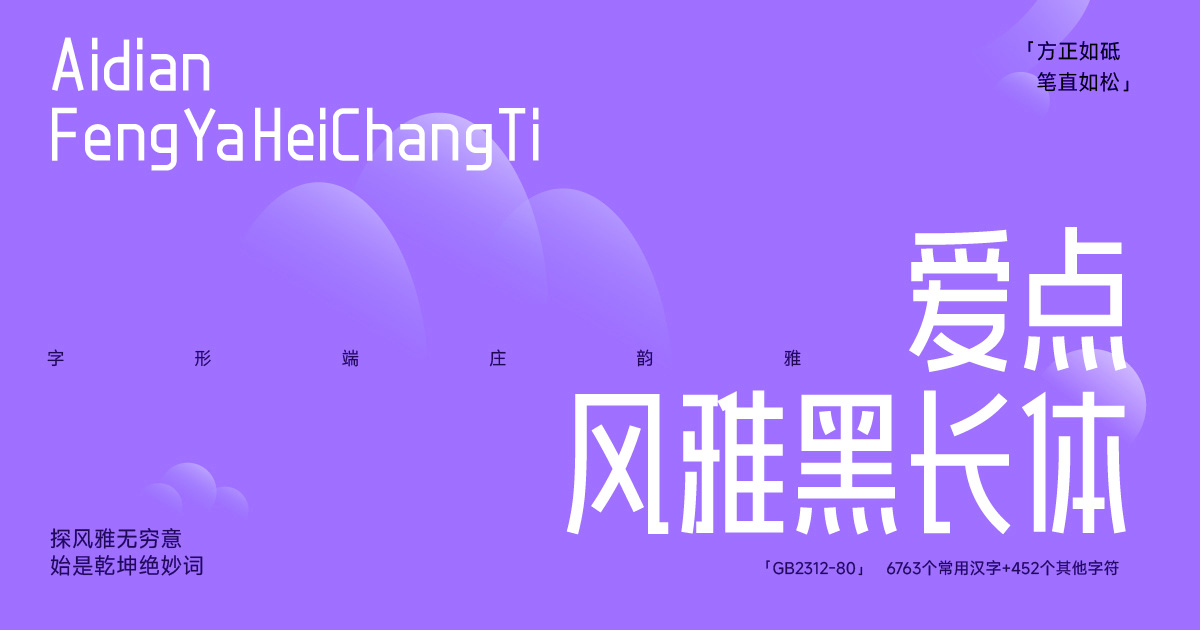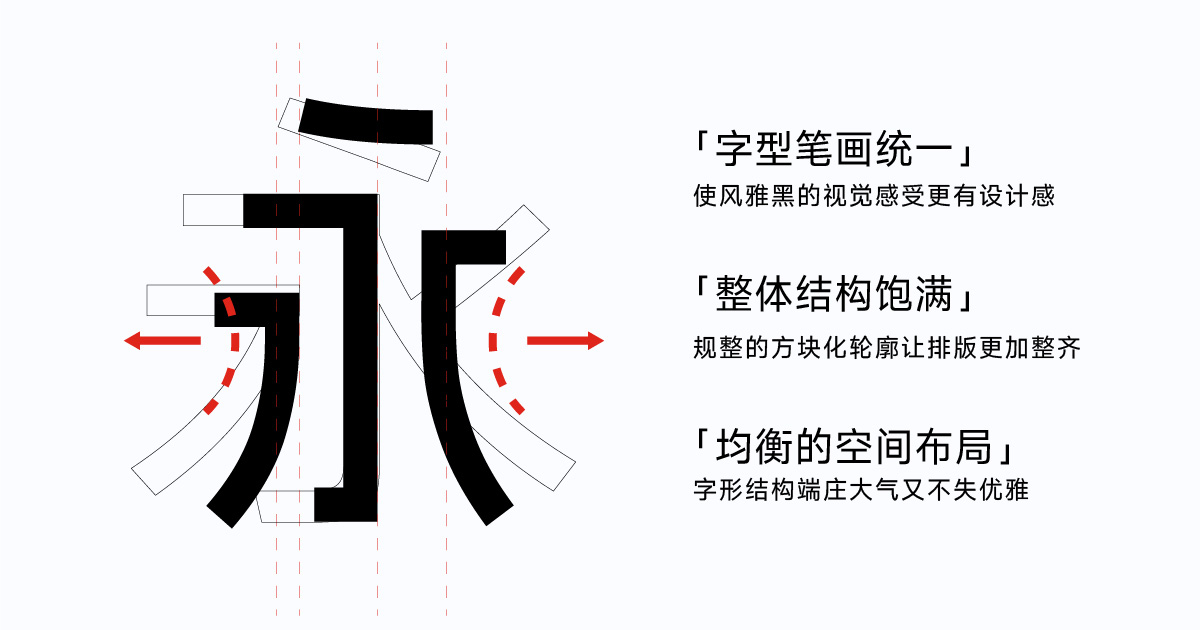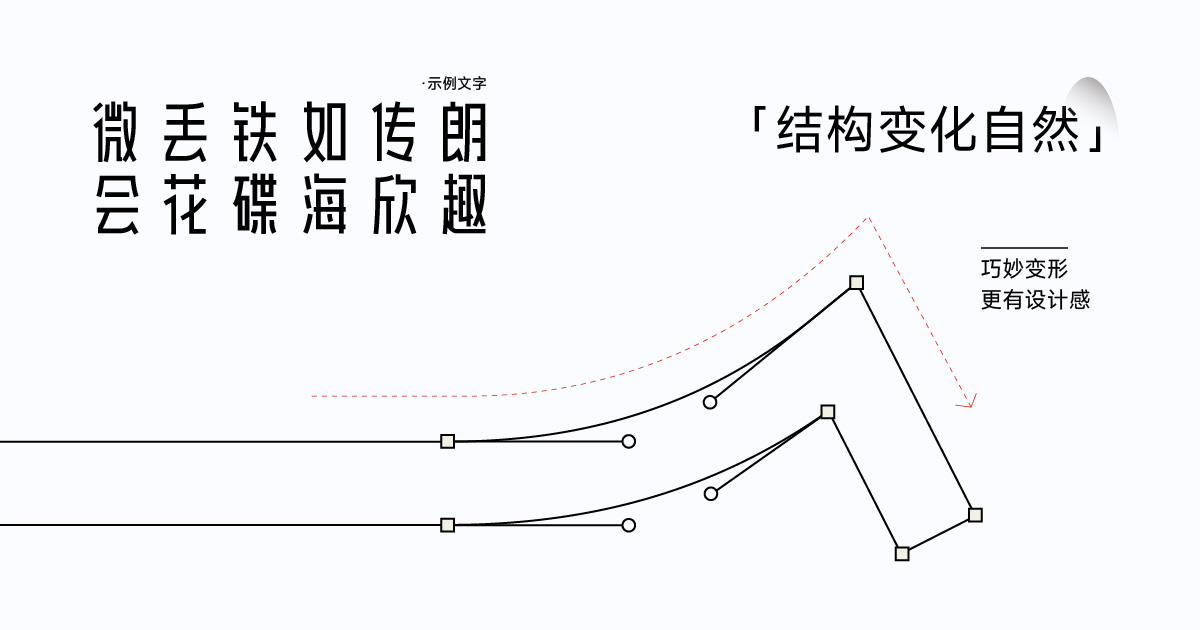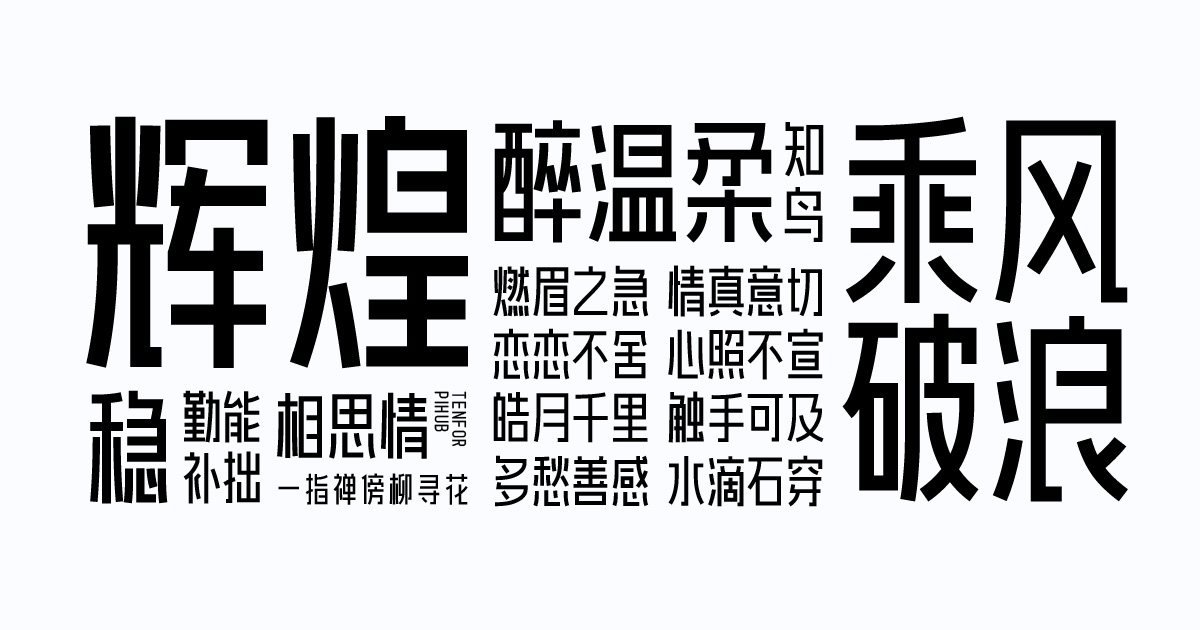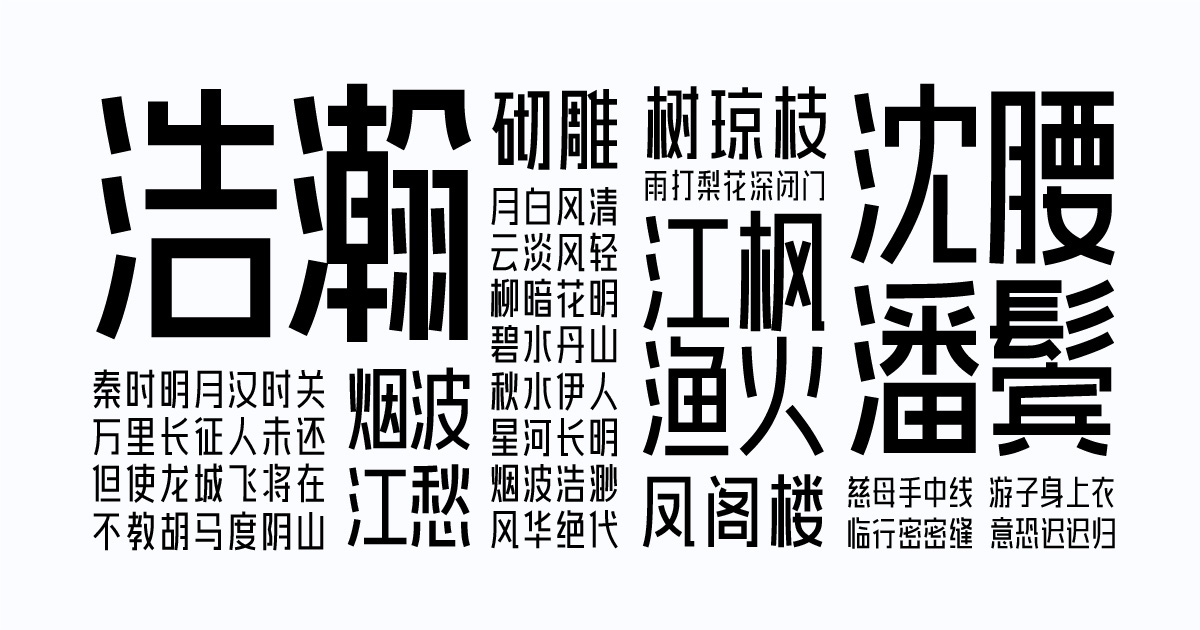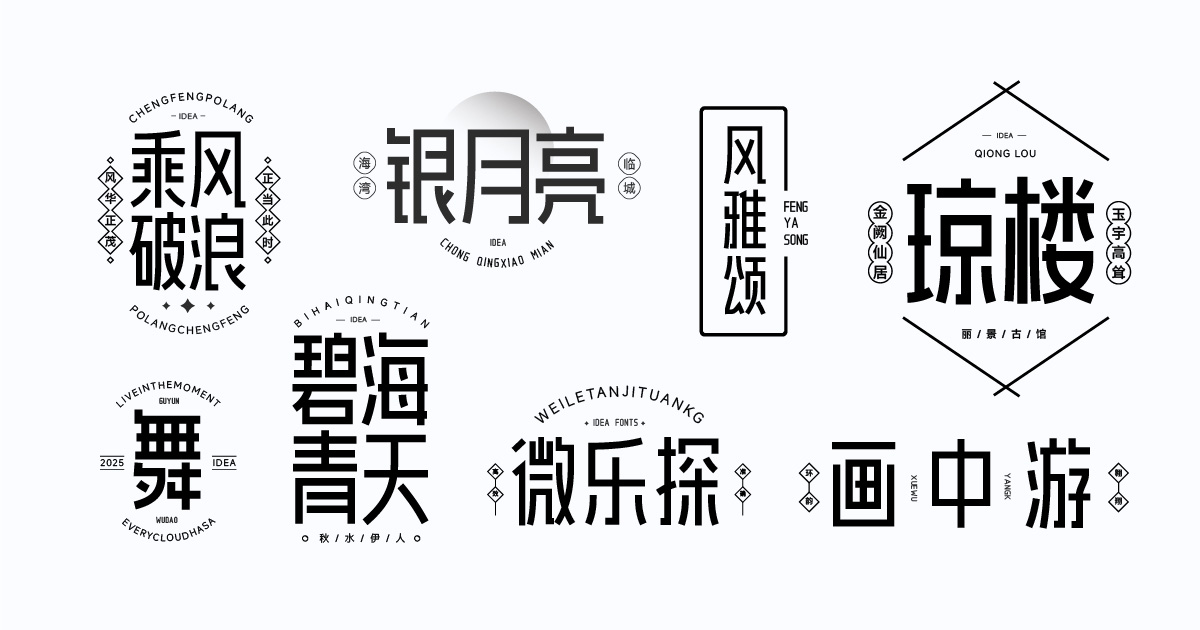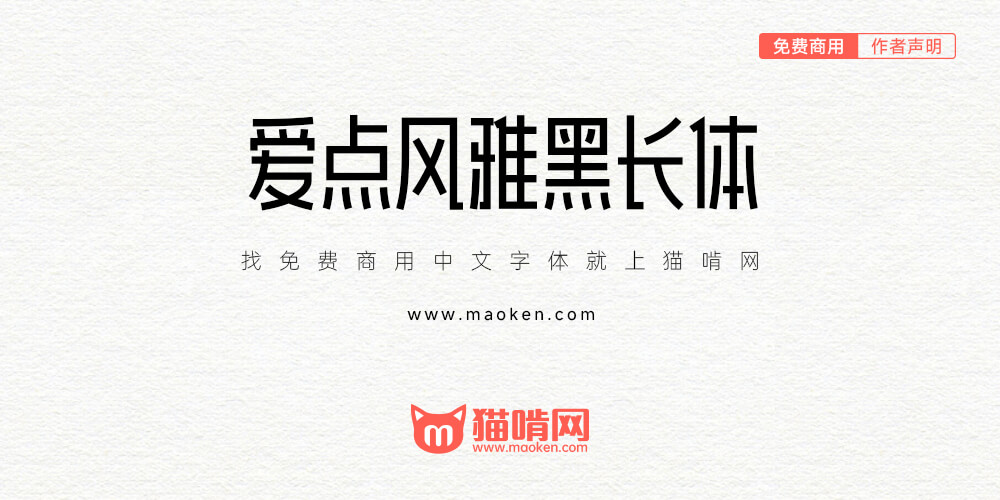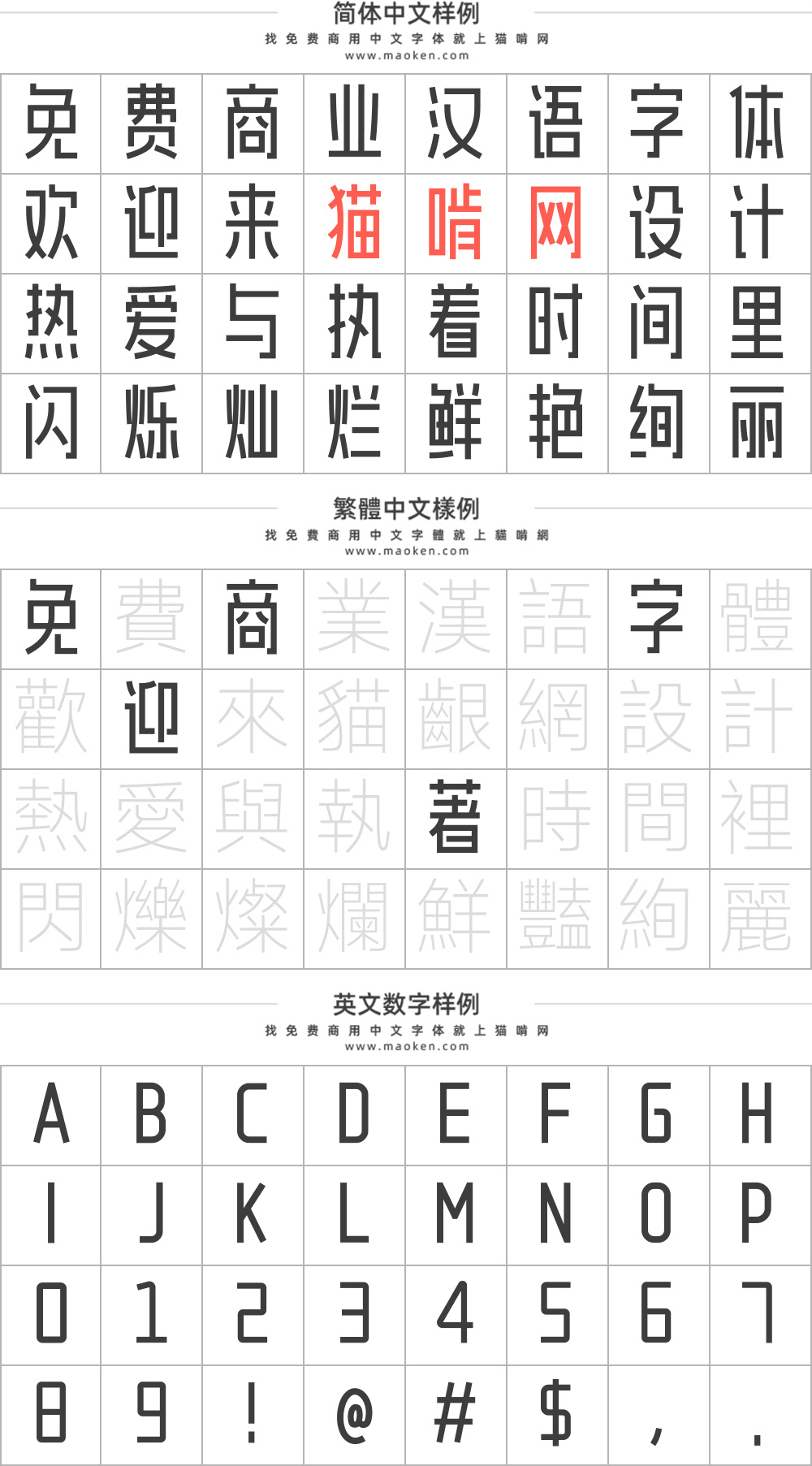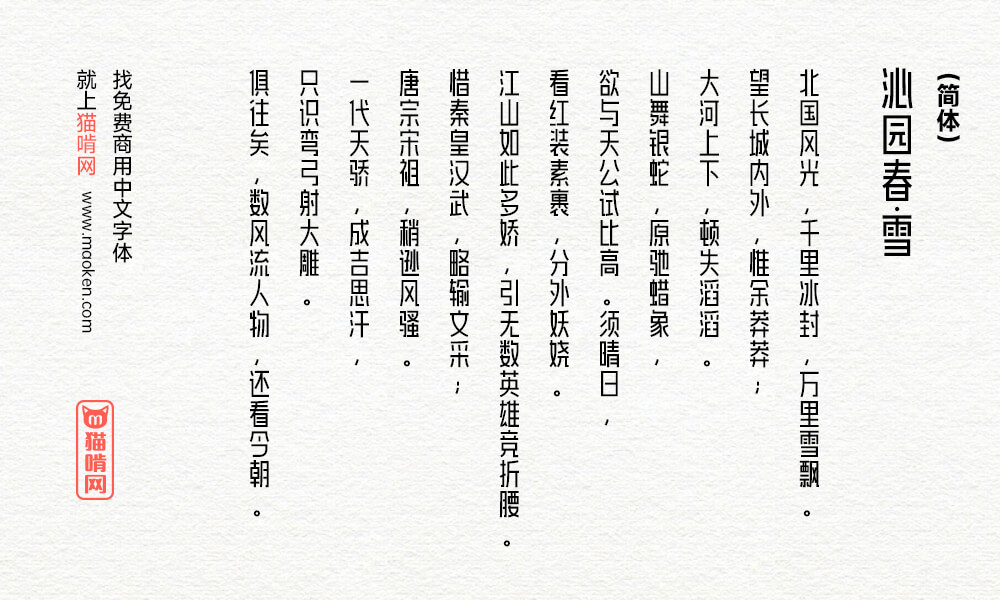
爱点风雅黑长体:基于“爱点风雅黑”研发的系例免费商用字体
爱点风雅黑长体是广州爱点视觉文化有限公司(爱点字库)基于“爱点风雅黑”研发的系例免费商用字体,个人及企业可永久免费使用。该字体高挑时尚,端庄韵雅,可免费用于各类平面设计、视频字幕等用途。
这个字体里面有错别字,狼字变成了狠字
輸入繁體並不能顯示繁體啊!
• 这本来就是简体字体好吗!
• This font is only for Simplified Chinese!